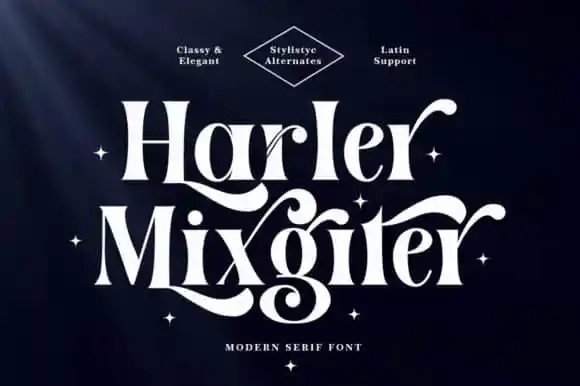
Harler Mixgiter Serif Font – Download Grátis
A Harler Mixgiter Serif Font é uma opção versátil para designers que buscam elegância moderna em seus projetos digitais. Fabricada pela IM Studio, esta fonte possui um estilo único, com alternativas e ligaturas que adicionam profundidade aos textos. Ideal tanto para aplicações de design de mídia impressa quanto para a criação digital, essa fonte é perfeita para headlines, convites, logotipos ou até mesmo projetos relacionados ao casamento. Com uma gama extensa de alternativas e letras em forma de doodle disponíveis, você pode combinar essas opções criativas para criar designs únicos e encantadores. Esta atualização oferece a escolha entre sete combinações de peso e largura para cada traço, ou permite que você faça ajustes personalizados usando o formato variável OTF (OpenType Font). A Harler Mixgiter inclui letras maiúsculas e minúsculas, números, ligaduras, contornos acidentados, símbolos e ornamentações, tornando-a uma opção flexível para qualquer tipo de projeto gráfico.